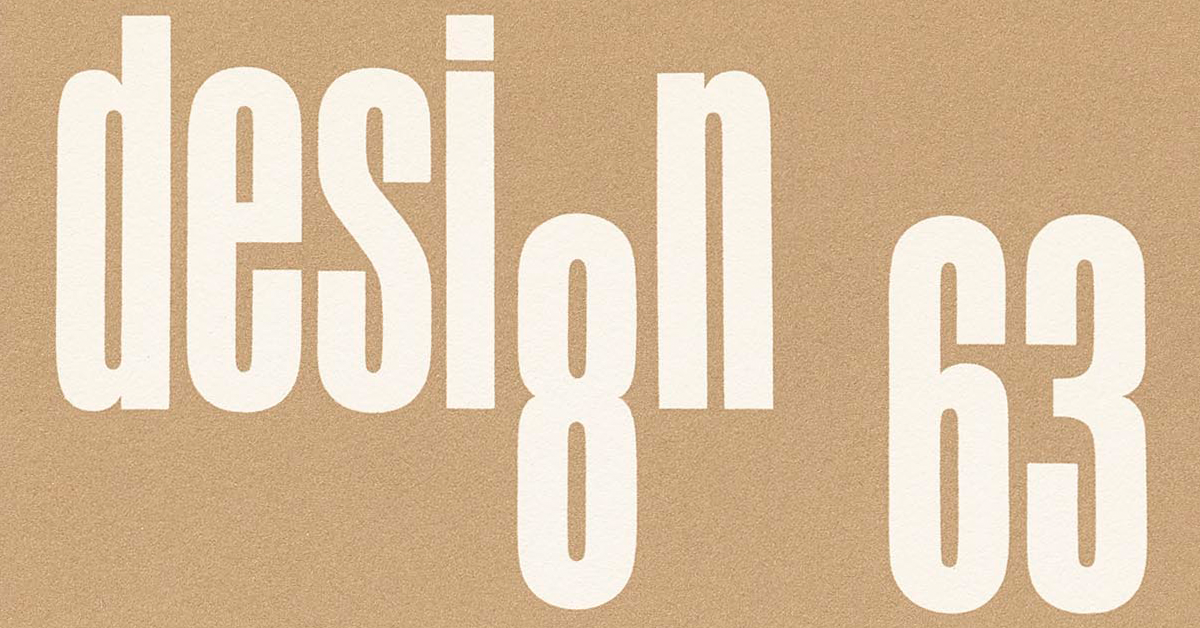
Letterform Archive: mil años de tipografía en línea
Inspírate con la colección digital en alta calidad de tipografía de Letterform Archive
Letterform Archive fue fundado por Roa Saunders, un coleccionista de arte en tipografía que deseaba compartir su colección con el público. Esta institución ha sido un referente para más de diez mil visitantes en los últimos cinco años, quienes han disfrutado en persona de una diversa colección de tipografías, caligrafías, textos y obras de arte.
Para que puedas disfrutar de piezas tan diversas como una página del Corán del año 1150, o el diseño innovador de la revista Emigre, o carteles de la Segunda Guerra Mundial, han puesto su colección en línea.
El archivo fue preparado con los más altos estándares de luz, equipo fotográfico y alta resolución de archivos. Así podrás familiarizarte con las piezas y analizar cada trazo y estilo.
En sus palabras, el objetivo fue capturar todas las texturas de papel, la corrección de los artistas, impresión con tipos móviles, de modo que cada elemento se documentara en su forma esencial, no como una imagen plana, sino como un objeto que narra una historia.
Este sitio se diseñó pensando en los diseñadores gráficos, y tiene filtros de búsqueda para distintas disciplinas, firmas, personas, épocas y lugares.
En el sitio de Letterform Archive, también encontrarás otros recursos para entusiastas y profesionales de las letras, incluyendo kits de diseño y recomendaciones de documentales de tipografía.